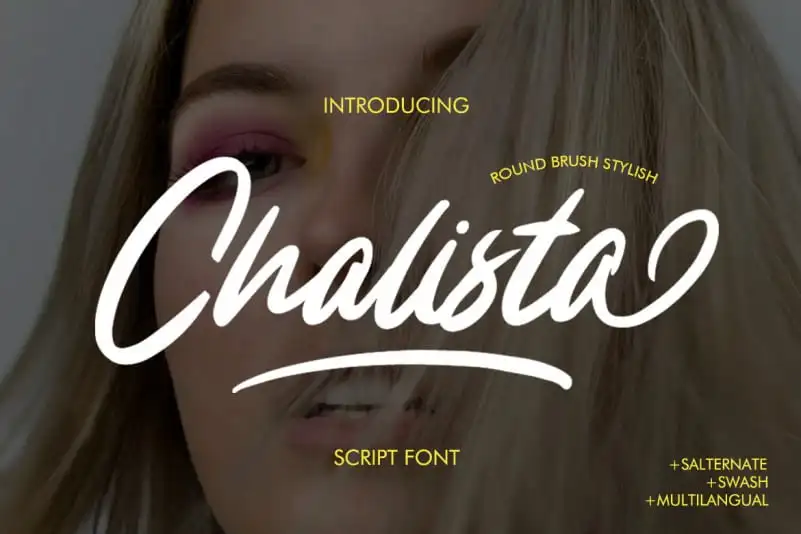
Chalista Script Font – Download Grátis
A Chalista Script é uma elegante fóntica com traços arredondados que se assemelham a escrita à mão, ideal para diferentes produtos, desde moda até fotografia. Desenvolvida pelo Wasisme Studio, essa fonte brush tem curvas únicas e confortáveis, perfeita para trazer um toque autêntico ao seu design. Seja você designer de moda querendo dar uma personalidade única a sua coleção de roupas ou fotógrafo procurando algo que se destaque entre outros trabalhos, Chalista Script oferece a oportunidade de tornar seus produtos singulares e marcantes. Suavemente curvada e arredondada, esta fonte brush é uma escolha ideal para quem deseja adicionar um toque autêntico à sua produção. Não hesite em explorá-la em seu próximo projeto!